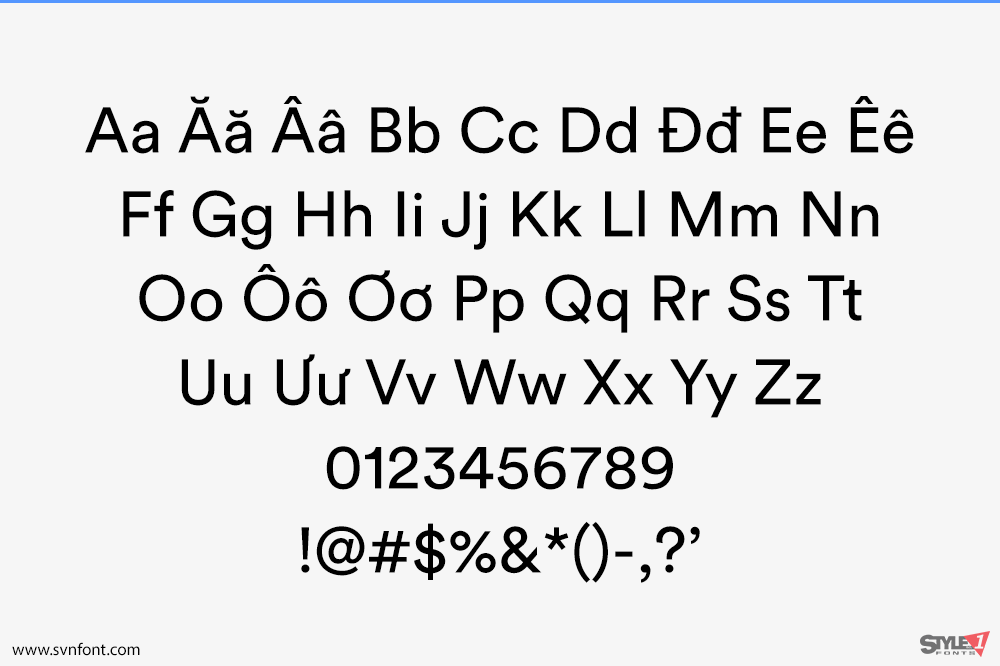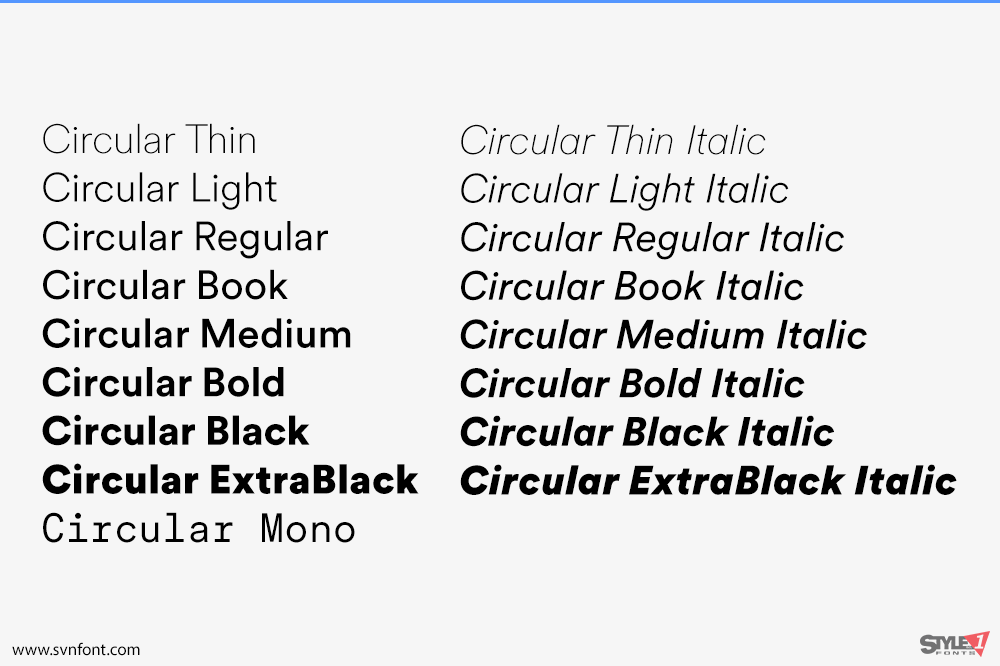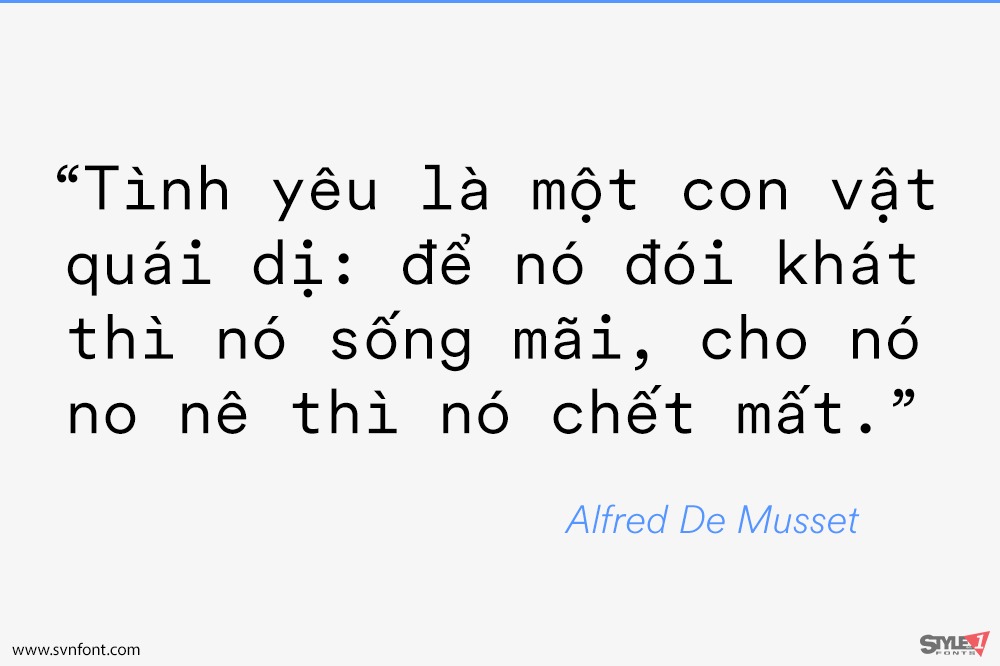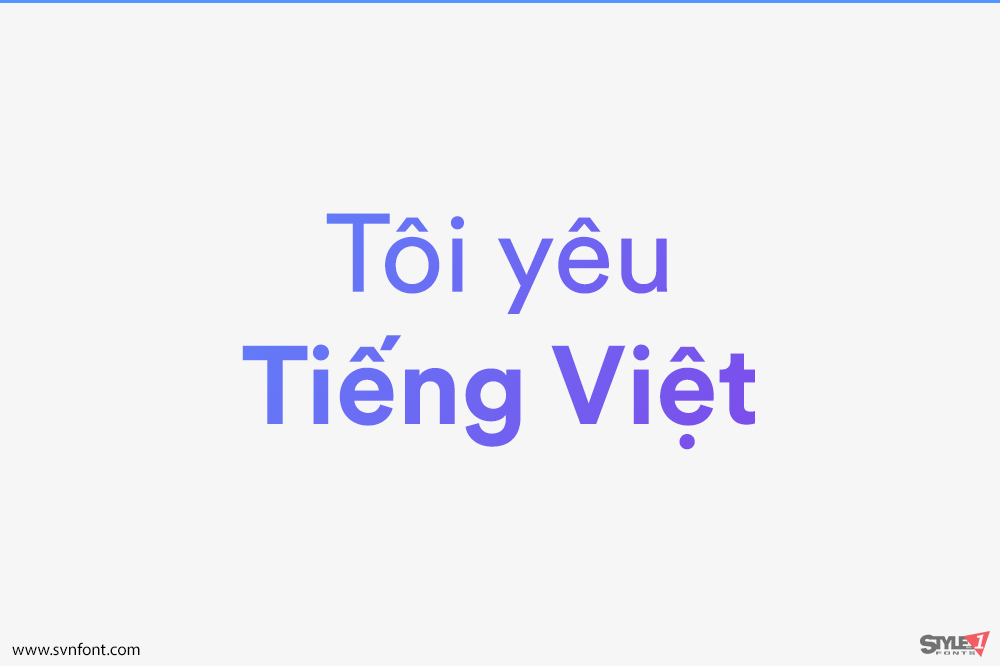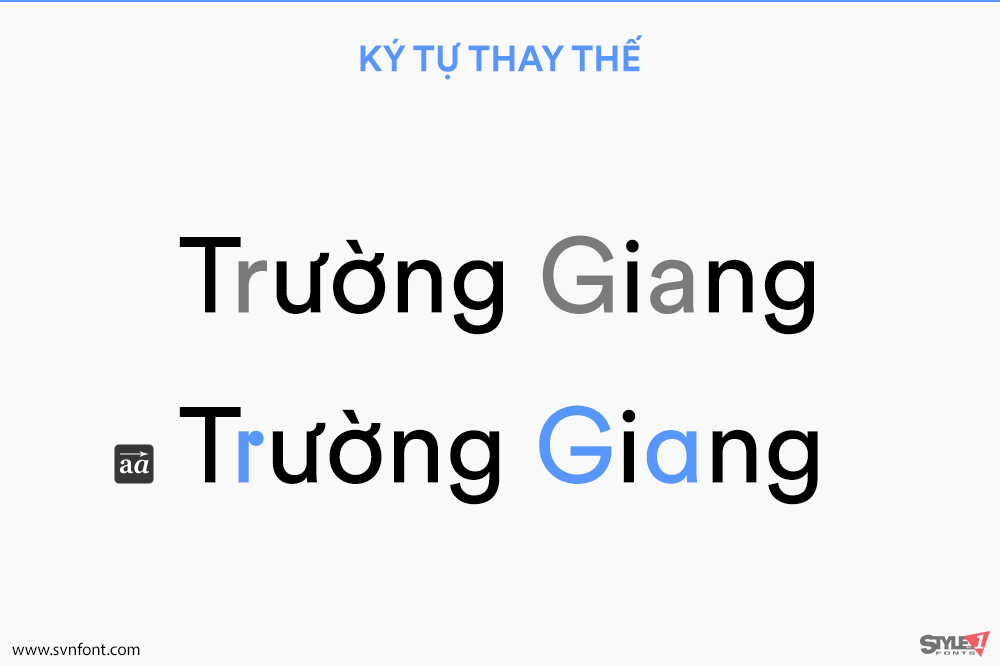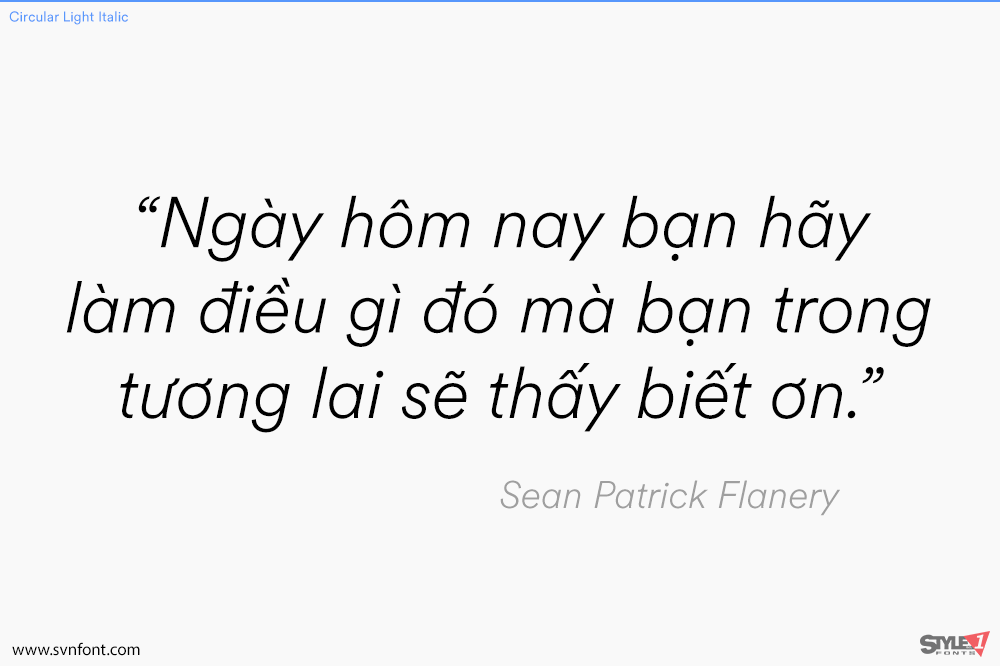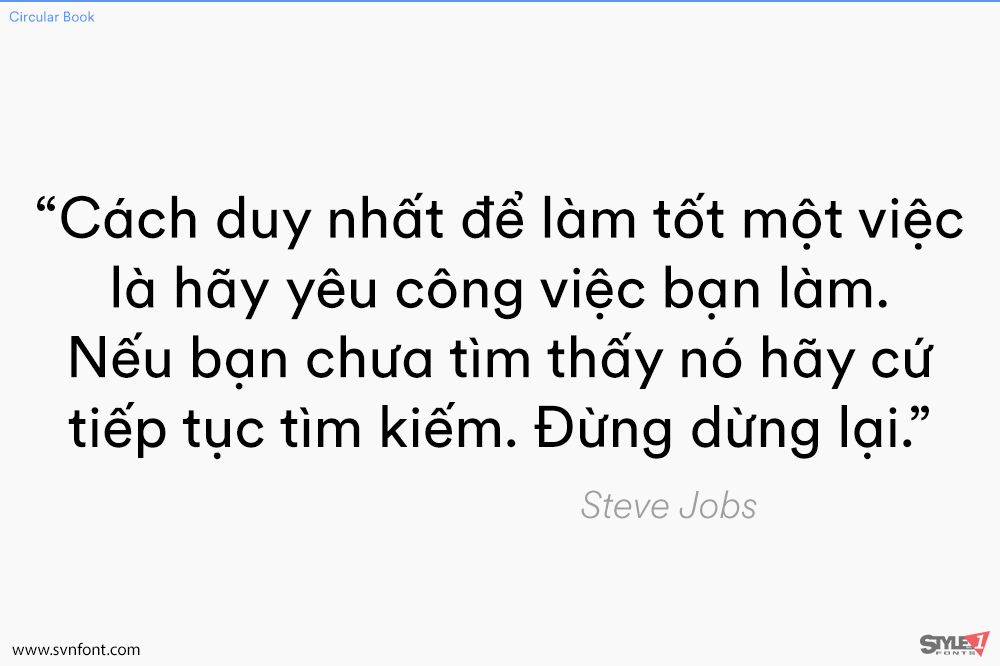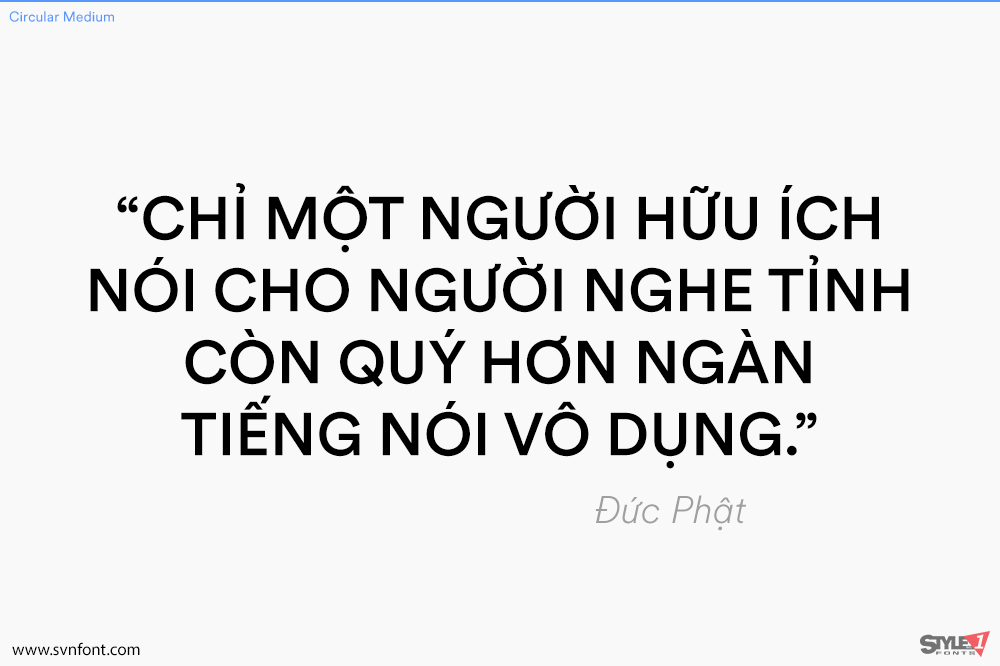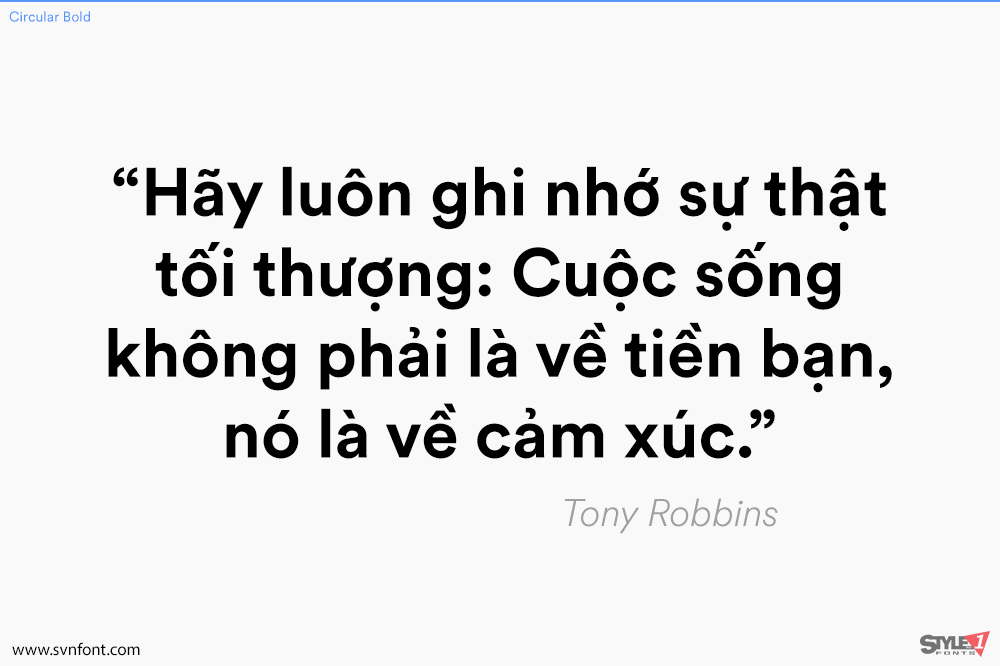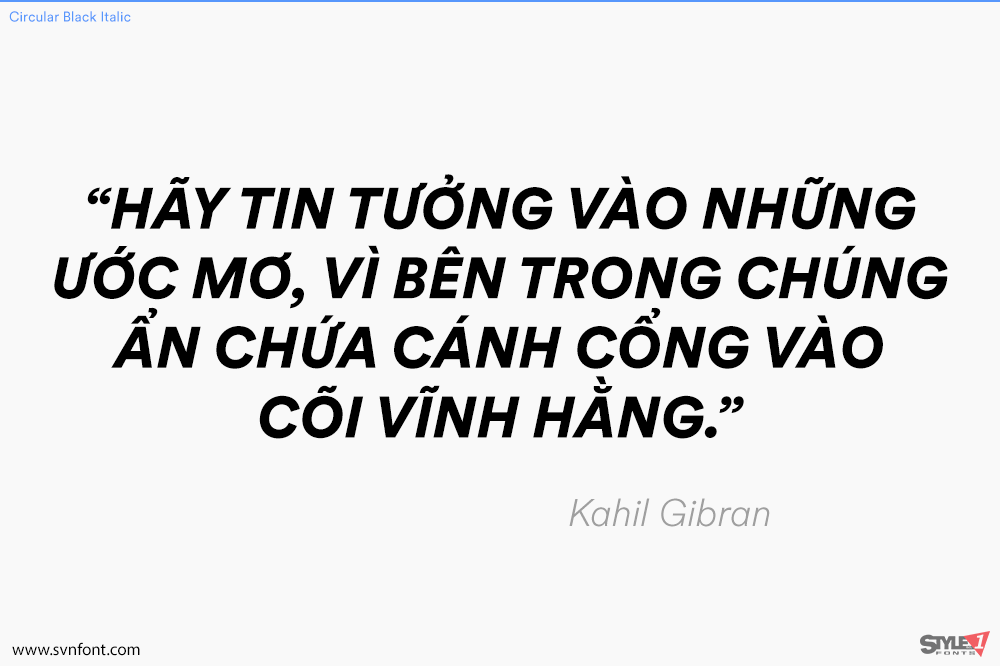
Circular là một kiểu chữ sans-serif hình học được tạo ra bởi nhà thiết kế người Thụy Sĩ Laurenz Brunner và phát hành thông qua Lineto vào năm 2013. Circular là sản phẩm chính thức thứ hai của Brunner, sau phông chữ Akkurat rất thành công.
Mặc dù thiết kế chủ yếu dựa trên các hình học cơ bản, Circular có những nét độc đáo mang lại sự ấm áp. Chữ ‘t’ viết thường trong phông này rất đặc biệt, giúp dễ dàng nhận ra Circular so với các phông sans-serif hình học khác. Circular có bốn độ đậm—book, medium, bold và black—mỗi độ đậm đều có kiểu chữ nghiêng tương ứng.
Nhà thiết kế: Laurenz Brunner
Nhà phát hành: Lineto